이모티콘 만들 때 상업적 이용 가능 무료 폰트 추천 17개
이모티콘을 만들 때에 그림을 그리기도 하고 알맞은 글을 써넣기도 하는데 그곳에 직접 글을 써도 좋지만 상업적으로 이용이 가능한 폰트를 사용해도 된다.
이모티콘 제작에서 폰트 선택이 중요한 이유
카카오 이모티콘 심사에서 글자 표현이 지저분하거나 가독성이 떨어지면 탈락 확률이 올라갑니다. 직접 손글씨를 쓰는 방법도 있지만, 잘 만들어진 폰트를 활용하면 완성도를 훨씬 빠르게 끌어올릴 수 있습니다. 단, 무료 폰트라도 “상업적 이용 가능” 범위가 폰트마다 다르기 때문에 이모티콘처럼 판매를 목적으로 한다면 반드시 라이선스를 확인해야 합니다. 아래 17개는 눈누(noonnu.cc) 기준으로 포장지·임베딩·BI/CI·OFL 범위가 모두 허용된 것만 선별했습니다.
상업적 무료 폰트 추천 17개
1. Gmarket Sans M
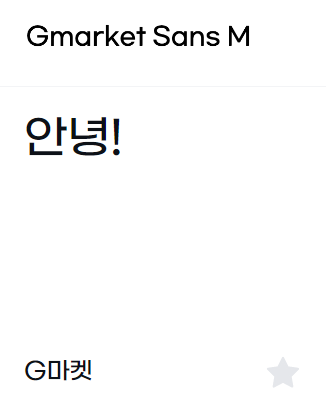
군더더기 없는 깔끔한 산세리프 폰트입니다. 텍스트 중심의 단정한 이모티콘이나 메시지형 이모티콘에 잘 어울립니다.
2. Gmarket Sans B
M보다 굵어서 강조나 임팩트 있는 한 마디 이모티콘에 좋습니다. “완전 동의”, “진짜?” 같은 반응형 이모티콘에 많이 쓰입니다.
3. 배민 주아체
동글동글하고 통통한 느낌이 특징입니다. 귀엽고 발랄한 캐릭터 이모티콘에 가장 자주 쓰이는 폰트 중 하나로, 처음 이모티콘을 만들 때 가장 먼저 시도해볼 만합니다.
4. 한나체Pro
굵고 개성 있는 획이 눈에 띕니다. 강한 감정 표현이나 유머러스한 이모티콘에 잘 맞고, 임팩트가 필요한 리액션 이모티콘에도 활용도가 높습니다.
5. 배민 도현체
거침없이 쓴 것 같은 손글씨 느낌이 매력적입니다. 솔직하고 직설적인 대화체 이모티콘, 또는 감정을 바로 내뱉는 스타일에 잘 어울립니다.
6. 중학생
실제 중학생이 쓴 것 같은 자연스러운 손글씨 폰트입니다. 투박하지만 친근한 느낌 덕분에 일상적인 감정 이모티콘에 잘 어울립니다.
7. 바른히피
살짝 기울고 자유로운 느낌의 손글씨 폰트입니다. 감성적이거나 꾸밈없는 분위기의 이모티콘에 개성을 더해줍니다.
8. 카페24 동동
동그랗고 밝은 느낌의 폰트로, 명랑하고 긍정적인 분위기의 이모티콘에 잘 어울립니다. 카페24에서 무료로 배포하는 폰트 시리즈 중 하나입니다.
9. 동글Bold
이름처럼 동글동글한 형태가 귀여움을 극대화해줍니다. OFL 라이선스로 자유도가 높으며, 귀여운 스타일의 이모티콘에 두루 활용할 수 있습니다.
10. 수줍은 대학생
실제 대학생이 쓴 것 같은 소심한 손글씨 폰트입니다. 내성적이거나 수줍은 감정 표현, “저 괜찮아요…” 같은 소극적 리액션 이모티콘에 딱 어울립니다.
11. 하나손글씨
하나은행이 배포하는 손글씨 폰트로, 정감 있고 따뜻한 느낌이 특징입니다. 일상적인 인사나 위로 메시지 이모티콘에 잘 어울립니다.
12. 느릿느릿체
천천히 쓴 것 같은 여유로운 손글씨 폰트입니다. 느긋하거나 게으른 캐릭터, 또는 ”…천천히 할게요” 같은 여유 있는 반응 이모티콘에 잘 맞습니다.
13. 장미체
부드러운 곡선의 감성적인 폰트입니다. 로맨틱하거나 따뜻한 분위기의 이모티콘을 만들 때 특히 잘 어울립니다.
14. 달의궤도
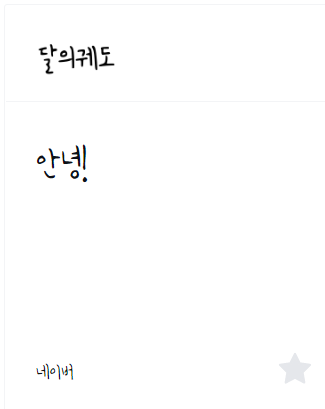
몽환적이고 독특한 느낌의 폰트입니다. 평범한 스타일에서 벗어나 개성 있는 이모티콘을 만들고 싶을 때 시도해볼 만합니다.
15. 미니 손글씨
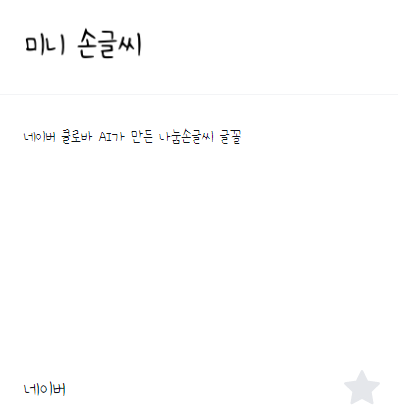
아담하고 깜찍한 손글씨 폰트입니다. 작은 텍스트가 들어가는 세밀한 이모티콘이나, 귀엽고 소소한 일상 감정을 표현하는 데 잘 어울립니다.
16. 또박또박
이름처럼 정확하고 또렷하게 쓴 느낌의 손글씨 폰트입니다. 가독성이 좋아서 짧은 텍스트를 강조해야 하는 이모티콘에 잘 맞습니다.
17. 둘기마요Medium
비둘기처럼 순하고 귀여운 느낌의 폰트입니다. OFL 라이선스로 자유도가 높으며, 귀여운 분위기의 이모티콘 전반에 두루 활용할 수 있습니다.